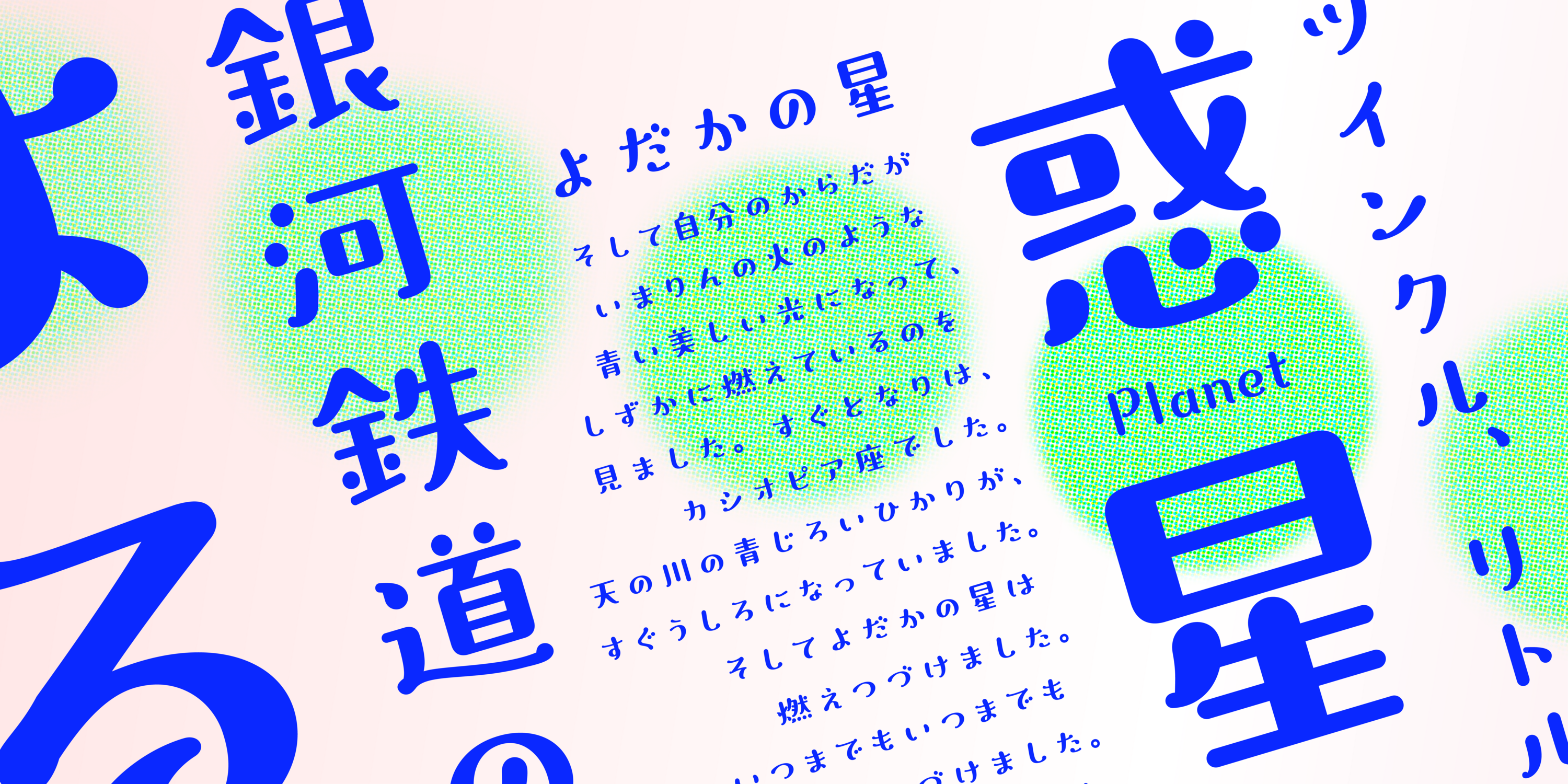
Monotype、新コンセプトフォント6書体を「フォントワークス LETS」「Monotype LETS」に追加
米国 Monotype Imaging Inc.の日本法人Monotype株式会社(東京都港区、以下 Monotype)は、Monotypeの提供するフォントサービス「フォントワークス LETS」「Monotype LETS」に新書体(全6書体)を新たに追加しました。
M Cute J
M Cute Jは、中国語フォントM Cute HKのデザインを元に制作した新しい日本語書体です。
文字の上部にしっかりとしたボリュームを持たせ、下部はコンパクトにまとめることで、少し抜けたコミカルでユニークな表情を生み出しています。
エッジには丸みを持たせ、やさしさや温かみが感じられる、幼くてかわいらしい雰囲気が特徴です。
漢字はM Cute HKをベースにし、仮名もそのスタイルを踏襲しつつ、個々の文字がそれぞれ個性的な表情を持っています。
POPやフライヤー、ポスター、広告バナーなど、楽しい雰囲気づくりにぴったりです。遊び心やかわいらしさを演出したい場面で活躍する書体として、幅広い用途でご利用いただけます。
ネクタイノート
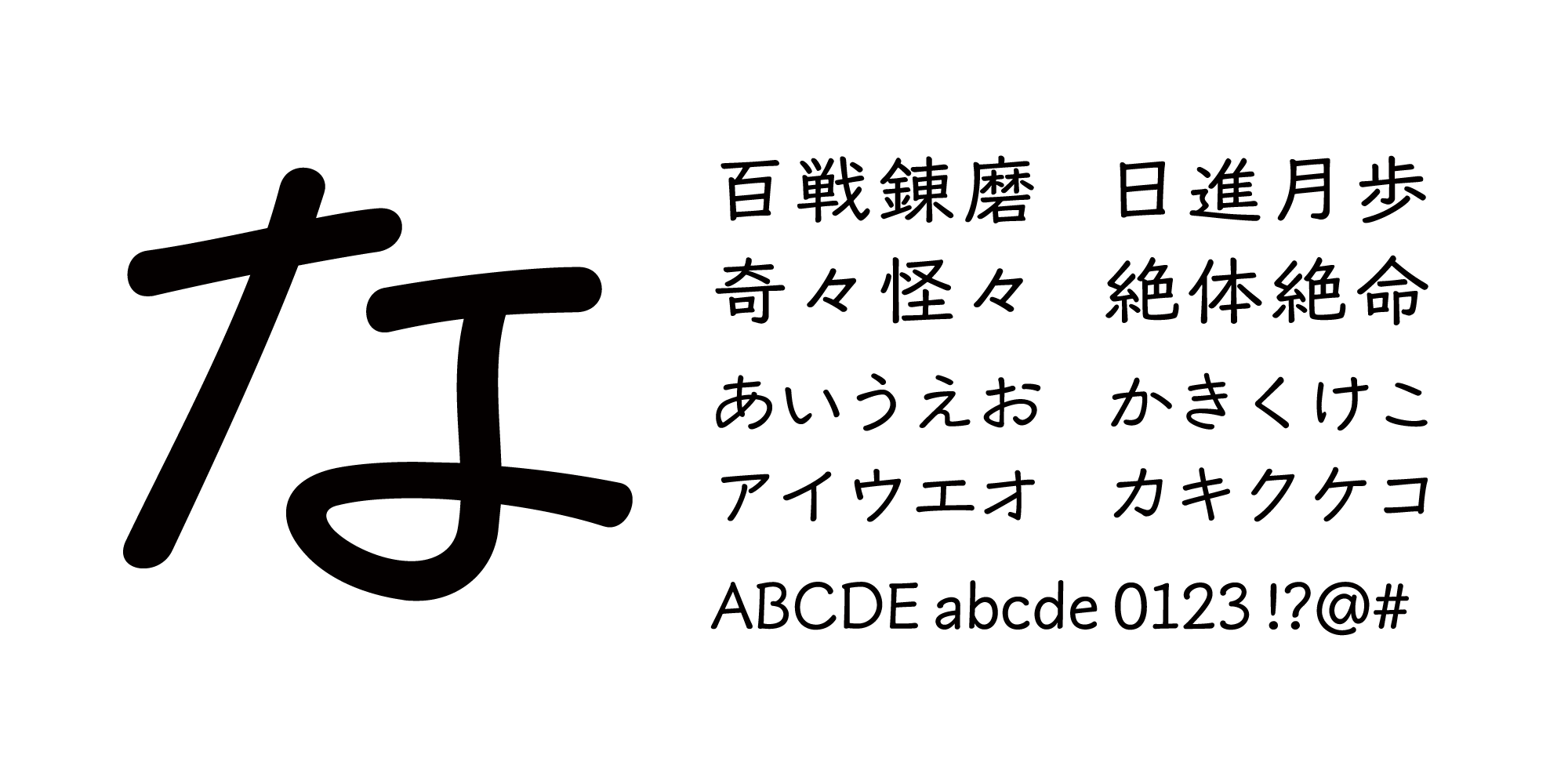
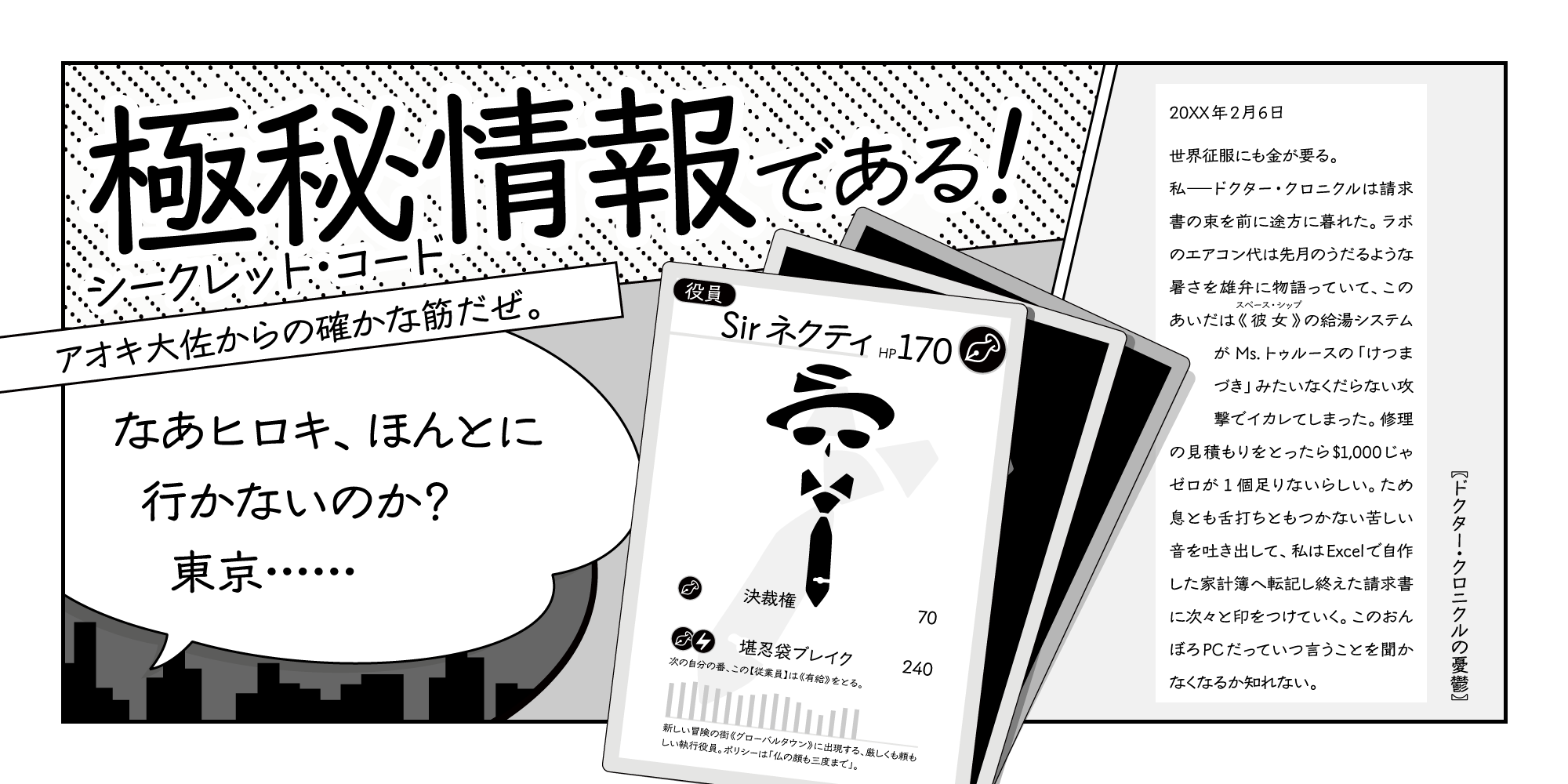
ネクタイノートは、アメコミなどのふきだしにぴったりの、語りのような味わいがある手書き風書体です。素朴さのなかに一定の緊張感が出る雰囲気をめざしています。
崩しすぎない自然な漢字に、ひとクセありながらも読みやすいひらがなとカタカナが組み合わさっています。
大人がギュッとすばやく・丁寧に書いた文字をイメージしていて、文章を組むと独特の疾走感やそばで話しかけてくるような味わいが生まれます。
コミックのふきだしはもちろん、エッセイや絵本の見出し・本文、ボードゲームの説明文などにもおすすめです。感情や思いをダイレクトに、そして穏やかに伝えたいときに最適です。
さゆびより
さゆびよりは、全ての力を抜いて書かれたような、リラックス感あふれる書体です。
控えめで穏やかなハネやハライのフォルムが、安らぎや脱力感を感じさせてくれます。
ぼんやりと気の抜けたような表情を持ち、見た人の心をほっと和ませ、緩さや穏やかな感情を自然と引き出します。
手作り感のある商品や、くつろぎ系のグッズ、愛らしいキャラクター雑貨などとも相性が良く、それぞれの魅力を和やかに引き立ててくれます。
また、観光案内パンフレットやフリーペーパーなど、地域や生活に密着した親しみやすさを演出したい場面にもおすすめです。
穏やかで物憂げな存在感が、ゆとりや癒しを表現したいシーンで活躍します。
こはるたいぷ
こはるたいぷは、ノートやちょっとした手紙などに書いたような手書き風のデザインを目指しました。どこか温かみがあって、飾らない自然な雰囲気を感じられるのが特徴です。
細いペンで書いたような揺らぎのある筆跡と丸みを帯びた書風は、軽やかなカジュアルさがあります。
また、1文字ずつバランスが異なっており、手書きならではの自然なムラを表現しています。
シンプルでありながらかわいらしいスタイルで、文章にすると全体的に柔らかくふんわりした印象を与えます。
優しさと親しみやすさを併せ持っているため、誰かに気軽にメッセージを伝えるときや、カジュアルなシーンで使うのにぴったりです。
ピコリコ
ピコリコは、軽やかなリズムの中に、親しみやすさと愛らしさを兼ね備えた書体です。縦画・横画のコントラストに加え、丸みのあるエレメントや小さめの字面、ゆったりとした間合いが全体にやさしく心地よいリズムを生み出します。
仮名は穏やかな曲線でかわいらしさを感じさせ、漢字は直線的な構造の中にやわらかさを取り入れました。欧文も日本語と調和し、デザイン全体に小さなアクセントを加えています。ファミリー向けコンテンツやキャラクターグッズ、教育分野など親しみやすく楽しい雰囲気を伝えたいデザインにおすすめです。
ロボタイプ
ロボタイプは、SFのロボットから着想を得たメカニカルでパワフルな書体です。シャープで幾何学的なデザインは変形するロボットのダイナミックさを表現しています。
漢字の上下には極太のストロークを不規則な角度で配置しました。比較的細い中間のストロークは、関節のある手足が軽やかに多方向に動く様子を想起させます。これらの要素が融合することで、力強く、洗練された存在感を発揮します。
また、英数字の高めの重心と、仮名の自由な傾きが、テキストに機械的でありながらもチャーミングな雰囲気を与えます。
タイトル、見出しなど、目立つ位置に大きく使う場面におすすめです。
【提供書体一覧】フォントワークス LETS(全6書体)
| 書体名 | ウェイト | デザイナー |
| M Cute J | Light | 山村 佳苗 |
| ネクタイノート | Regular | 中村 勇弥 |
| さゆびより | Demi | 森田 隼矢 |
| こはるたいぷ | Light | 越智 亜紀子 |
| ピコリコ | Demi | 寺内 なつ美 |
| ロボタイプ | Heavy | Monotype Studio |
対応字種は常用漢字、ひらがな、カタカナ、プロポーショナル欧文(英数字)、全角数字、一部の記号です。
Adobe Japan規格には準拠していません。